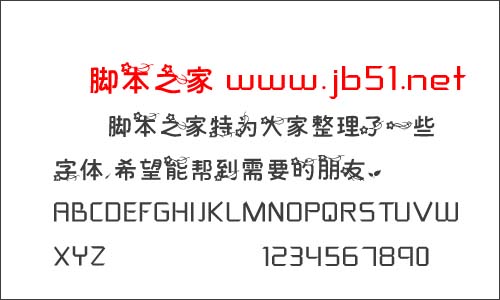
昨日星辰字體是一款用于創(chuàng)意設(shè)計方面的字體,該字體線條粗細(xì)適中,字形端正大方得體,整體風(fēng)格非常出色,并且字庫完整,可用于藝術(shù)設(shè)計、包裝印刷、簽名設(shè)計、圖形設(shè)計等領(lǐng)域,需要此款工具的朋友們歡迎前來下載使用。